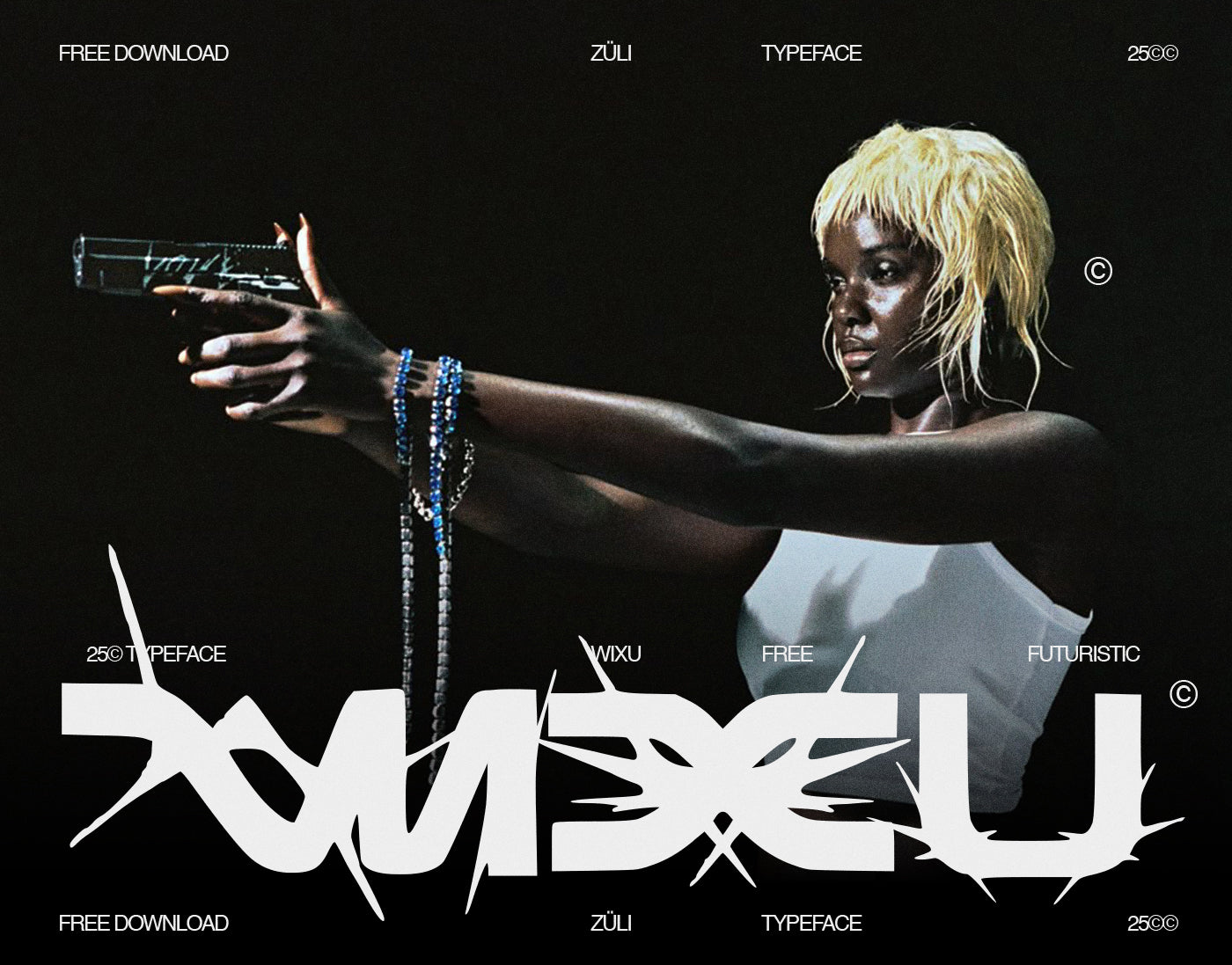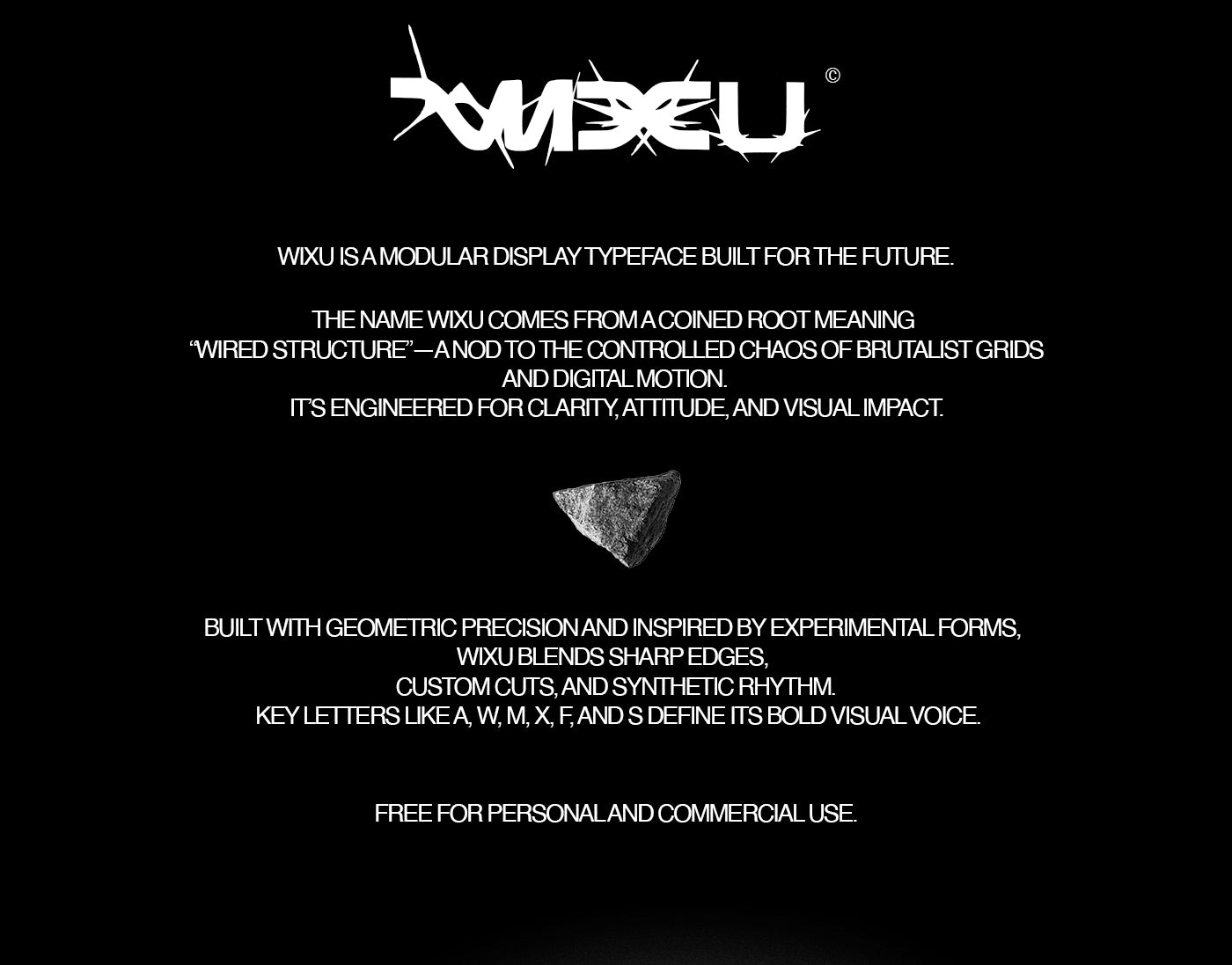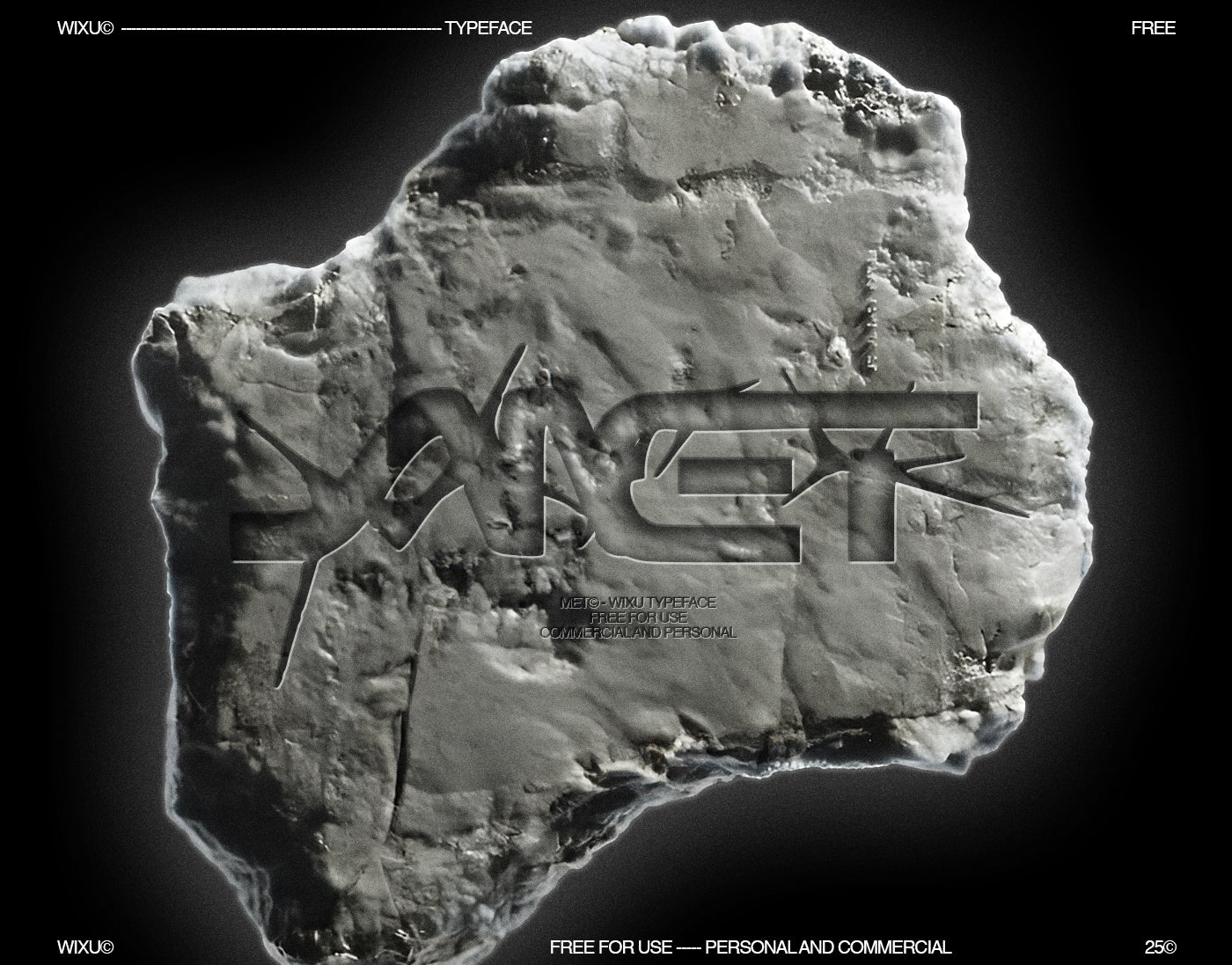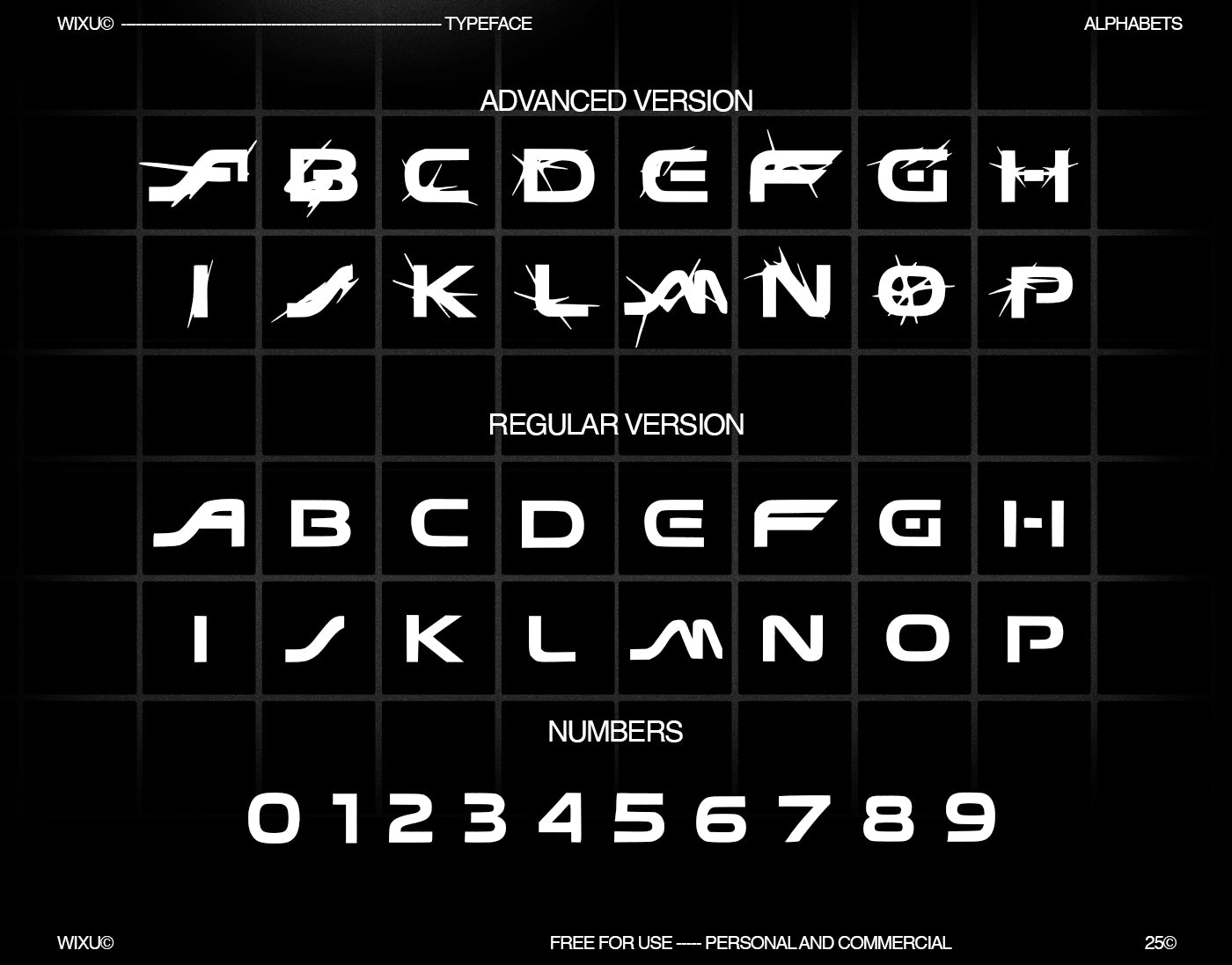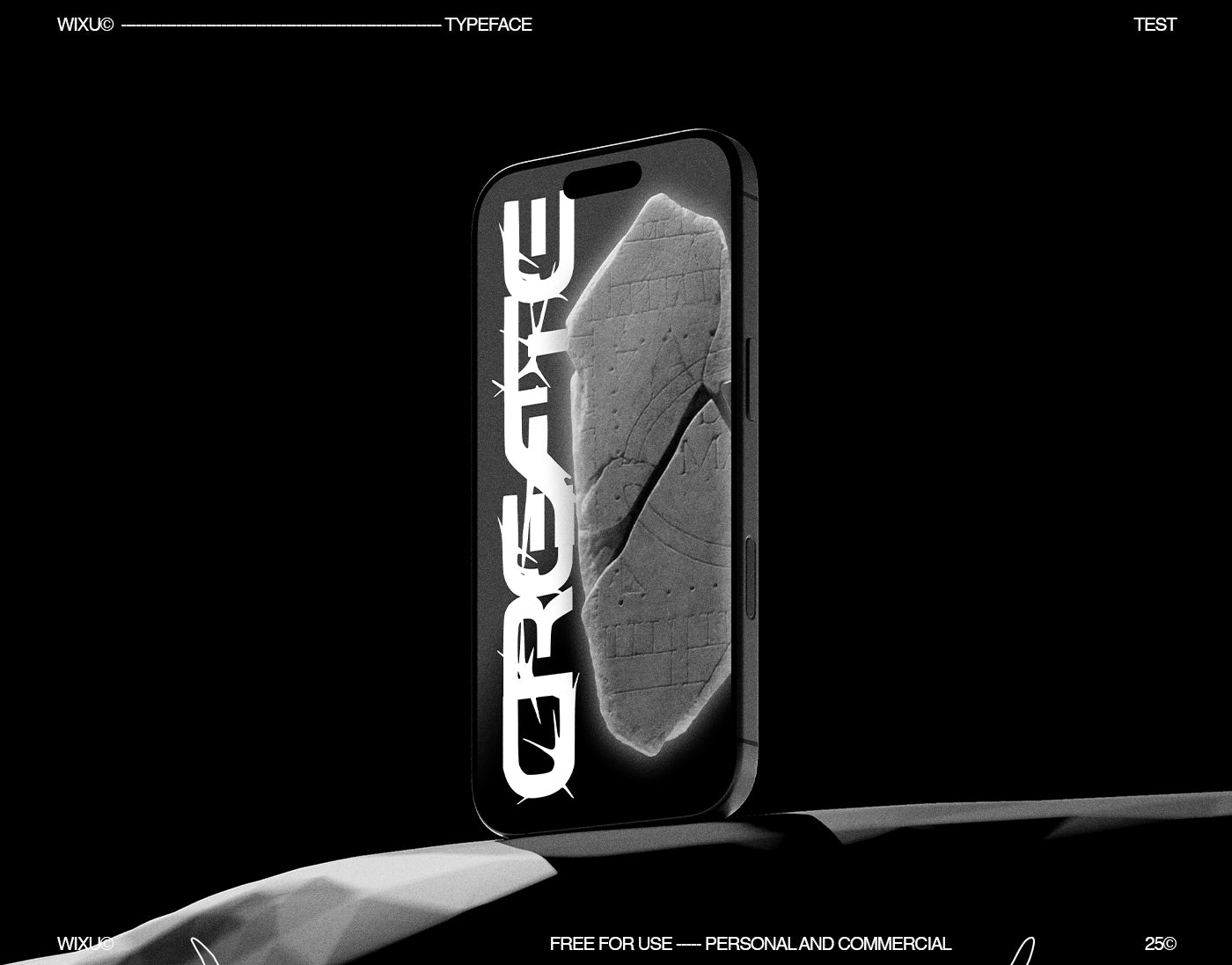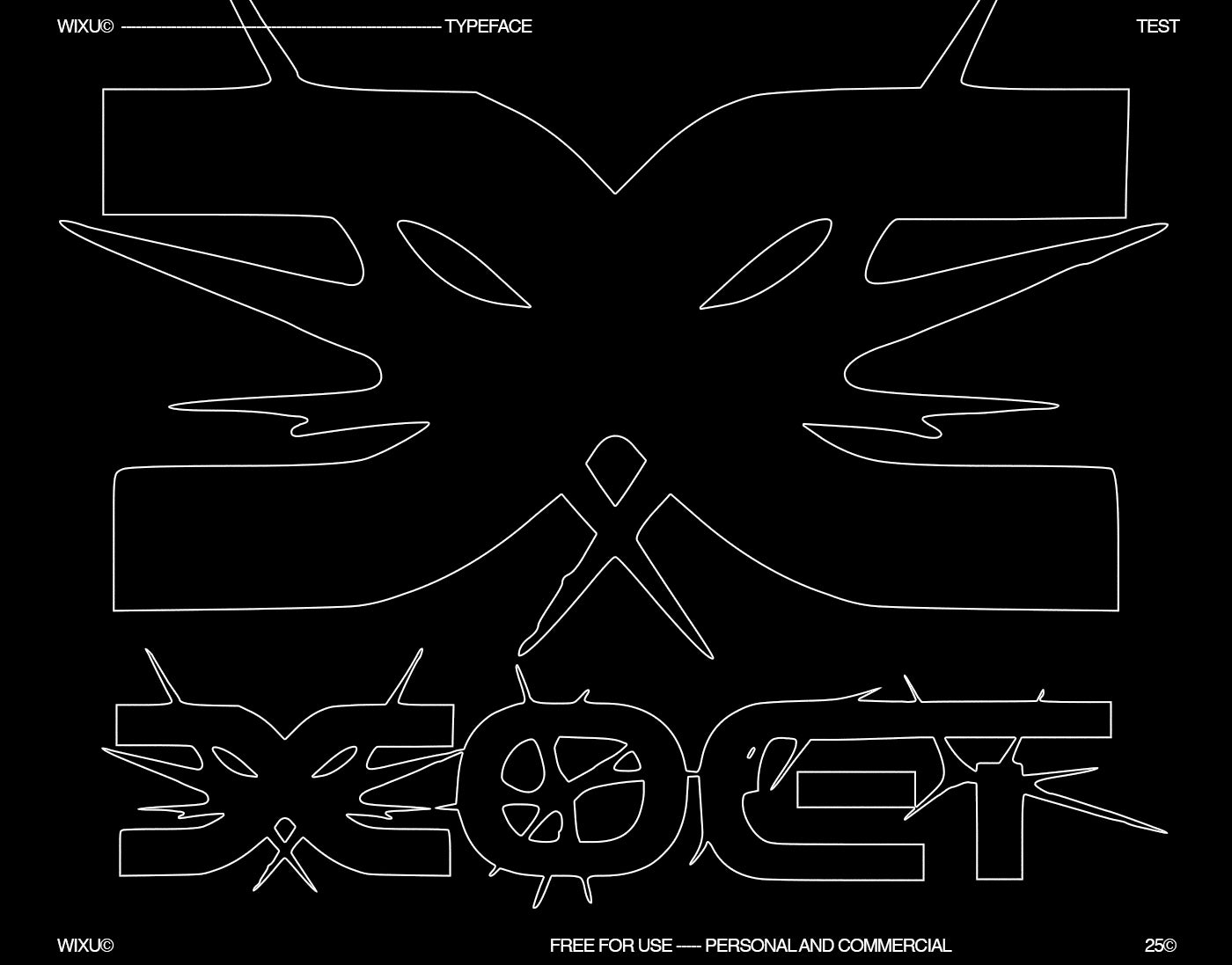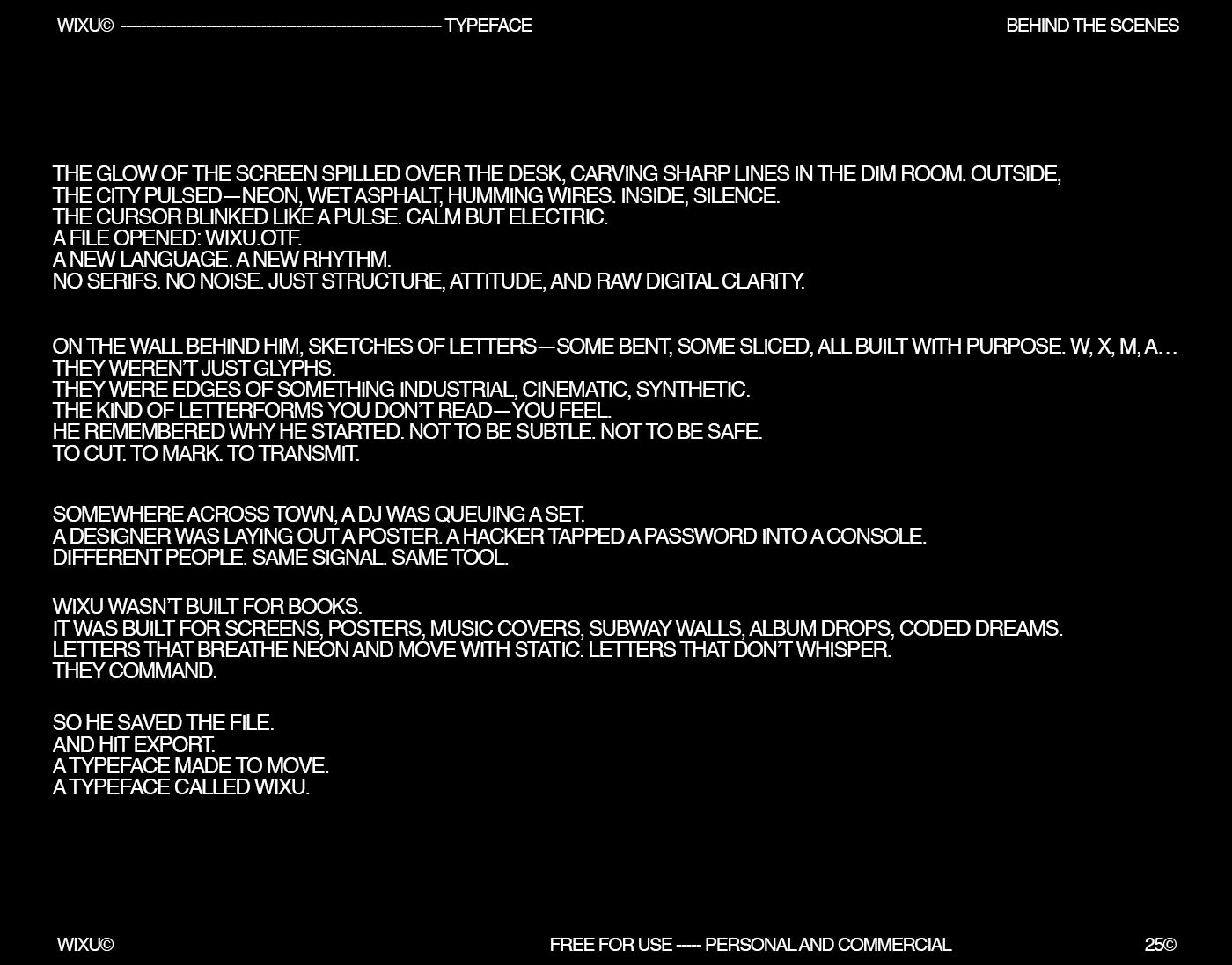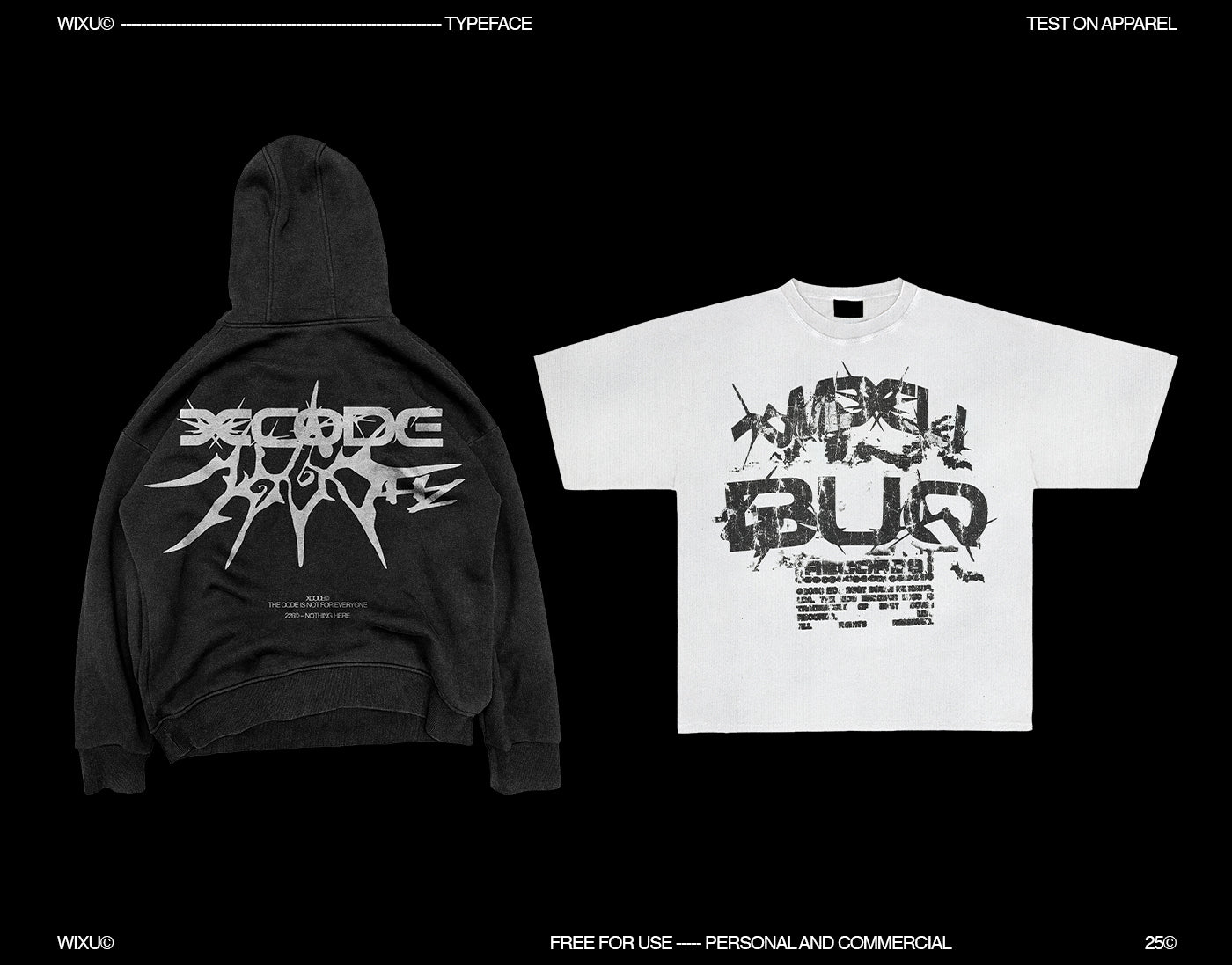
Wixu - Free Y2k Typeface| Züli
Préparez-vous à un voyage dans le temps avec cette police de caractères inspirée de l'esthétique Y2K. Avec son style futuriste et ses lignes audacieuses, elle est l'outil parfait pour donner à tous vos projets une touche unique et avant-gardiste.
Caractéristiques
Jeu de caractères complet : Inclut toutes les lettres (A-Z) et tous les chiffres (0-9), vous offrant une flexibilité totale pour n'importe quel design.